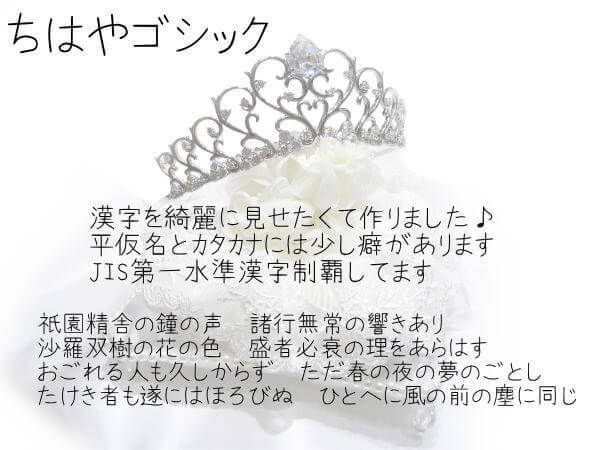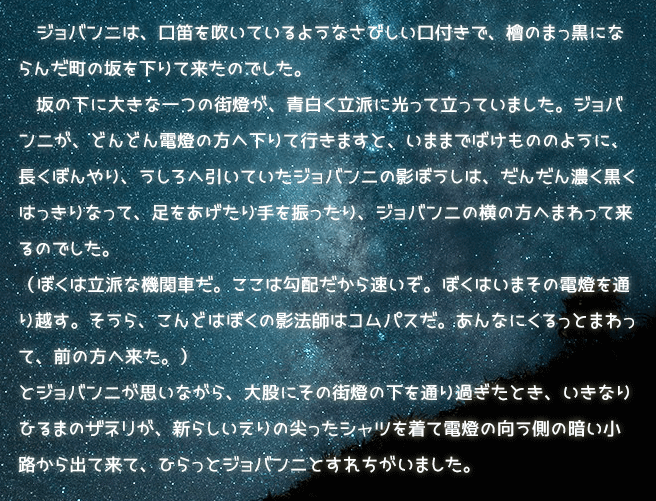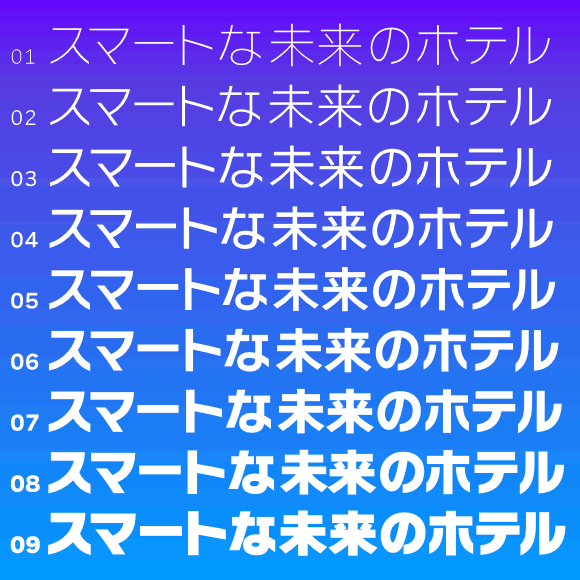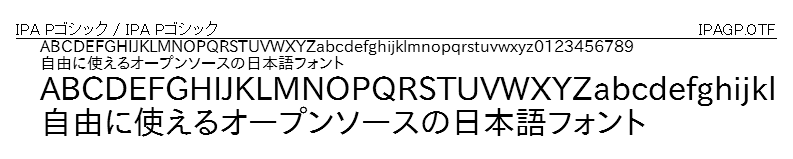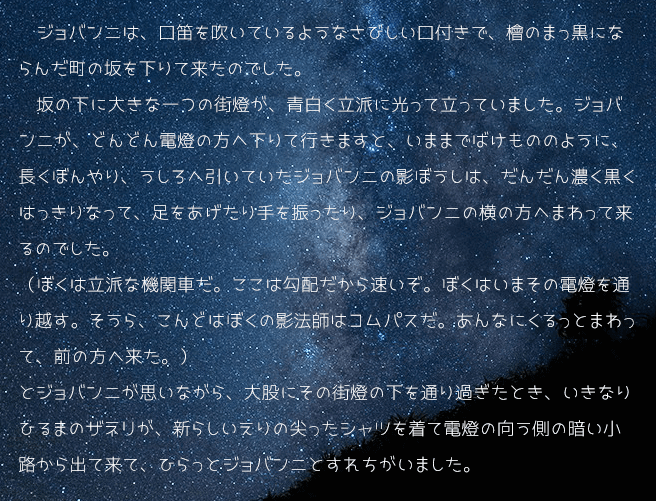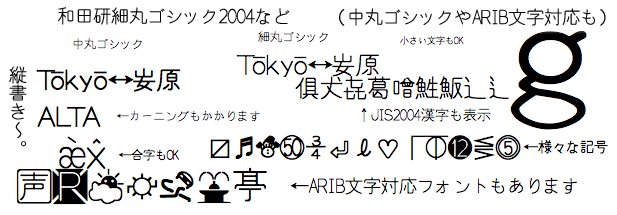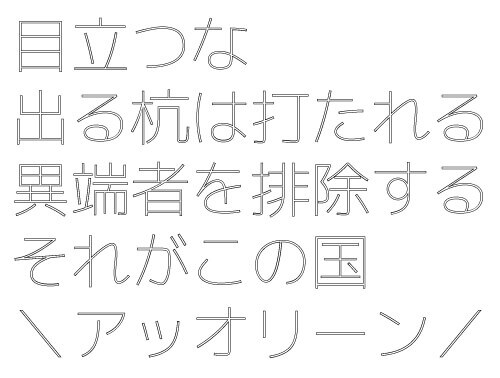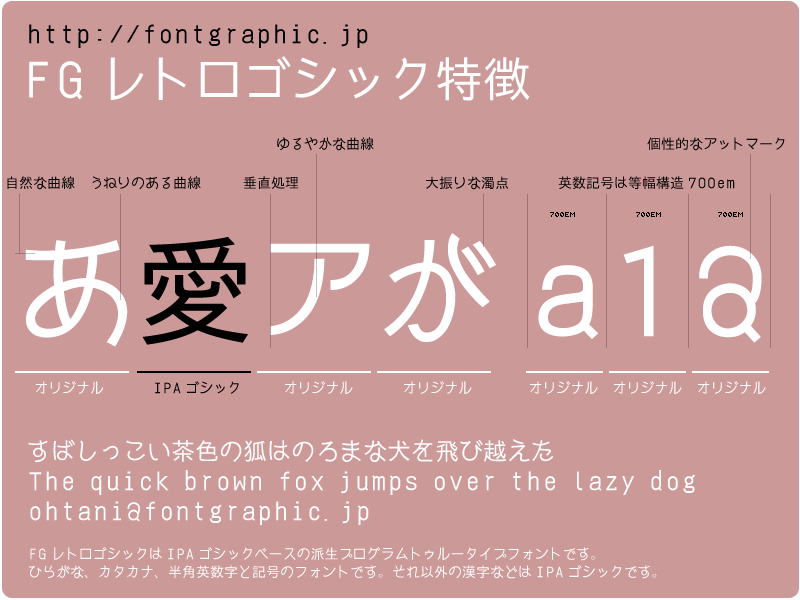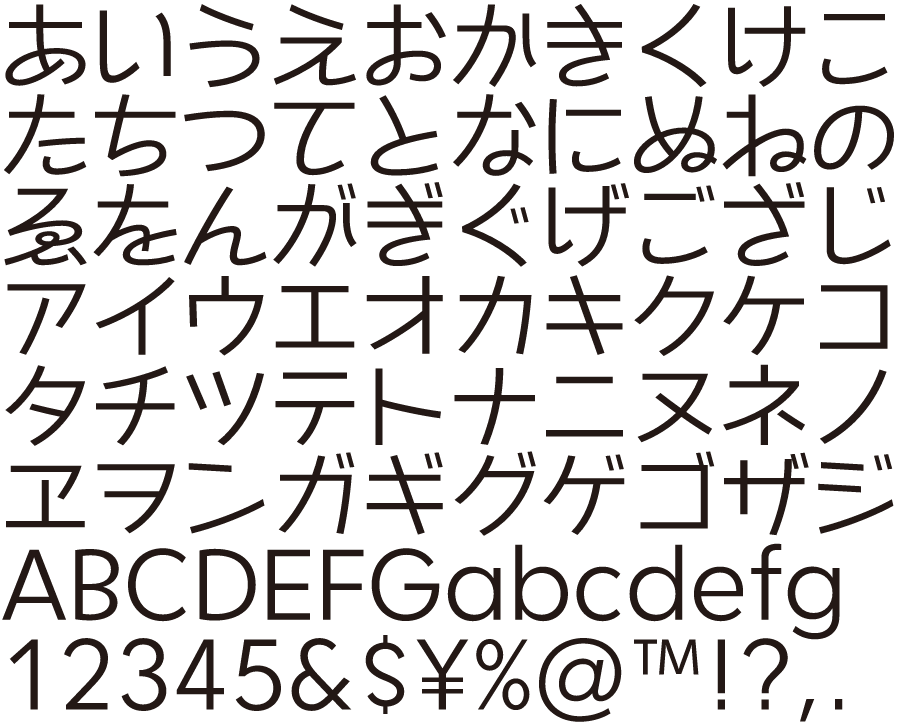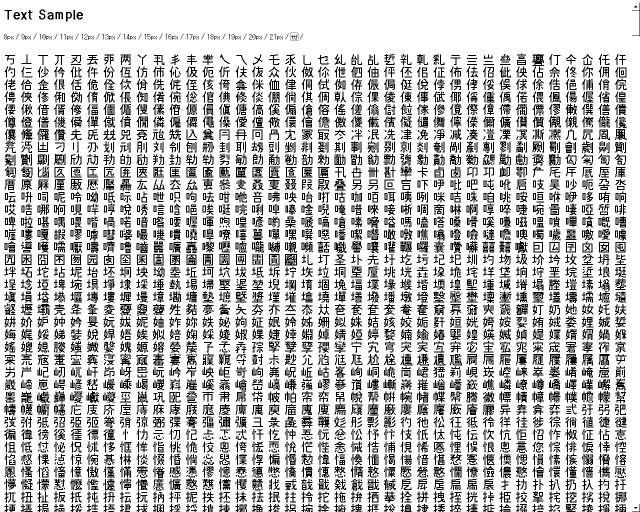
フリーで使えるゴシック体フォント43まとめ
フォントの中でもゴシック体は親しみやすく汎用性が高いフォントになっています。今回は、無料で使えるゴシック体フォントを43個集めました。同じゴシック体でも細いものや太いものなど、作者様ごとに特徴があります。制作するデザインに合わせてご活用ください。
GD-高速道路ゴシックJA
高速道路標識の文字に採用されている書体である道路公団標準文字を再現したフリーゴシック体。漢字はJIS第一水準を中心として収録しています。
IPA Pゴシック
“JIS X 0213:2004”をサポートし、商用・非商用に限らず無償で利用できる高品位な日本語フォントのゴシック体パック。
IPAexゴシック
和文文字(仮名や漢字など)は固定幅、欧文文字は文字幅に合わせた変動幅を基本とした実装を行われ、日本語文書作成の利便性の向上を目指したフォント。ゴシック体ver。
IPAゴシック
“JIS X 0213:2004”をサポートし、商用・非商用に限らず無償で利用できる高品位な日本語フォントのゴシック体。
JKゴシックL
平仮名・片仮名が女子高生風(?)な可愛いフォント。
JKゴシックM
「JKゴシックL」の「Medium」ウェイトバージョン。
Mgen+ (ムゲンプラス)
フリーフォントである「M+ OUTLINE FONTS」をベースに、これに含まれない漢字・記号のグリフを「源ノ角ゴシック (Noto Sans CJK / Source Han Sans の日本語部分」で補うことで、さらに豊富な漢字や記号を使えるようにした合成フォント。
Nasu
見た目が似ている文字を判別しやすくするフリーフォント。
NasuM
上記の「Nasu」の等幅フォント。
NTDトーマスかな
ちょっとアンバランスなひらがなが特徴のカジュアルなサンセリフかなフォント。
Rounded Mgen+
Rounded M+ をベースに、さらに豊富な漢字や記号を使えるようにした丸ゴシックフォント。
Uetenフォント
濁点を上に置いたフリーフォント。
VL Pゴシック
M+ アウトラインフォントベースのモダンゴシック体の日本語 TrueType フォント。
VL ゴシック
M+ アウトラインフォントベースのモダンゴシック体の日本語 TrueType フォント。
かんじゅくゴシック
熟成された味わいとレトロな雰囲気が魅力の書体。第二水準の漢字も含まれます。
キネ丸ボールド
うねりの効いた曲線がおちつき感、懐かしい印象を与えてくれるフォント。